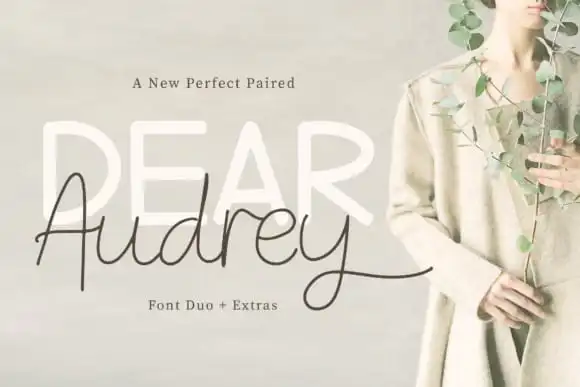
Dear Audrey Font Duo – Download Grátis
Introduzimos Dear Audrey Font Duo! Este é uma coleção de duas fuentes Script e uma fonte Sans Serif desenhada e compartilhada por PeterDraw. Com seu traço delicado e elegante, este duo de fuentes feitas à mão vai deixar seu projeto impecável. Use ambos os estilos juntos para personalizar seus trabalhos e impressionar seus leitores. Perfeito para cartazes, cartões de agradecimento, camisetas, materiais de marca, citações e qualquer outro projeto incrível que você esteja desenvolvendo. Cada fonte pode ser usada separadamente. Juntos, eles dão um toque leve e delicado com um ar vintage. Dear Audrey Font Duo é perfeito para projetos de design gráfico em geral.